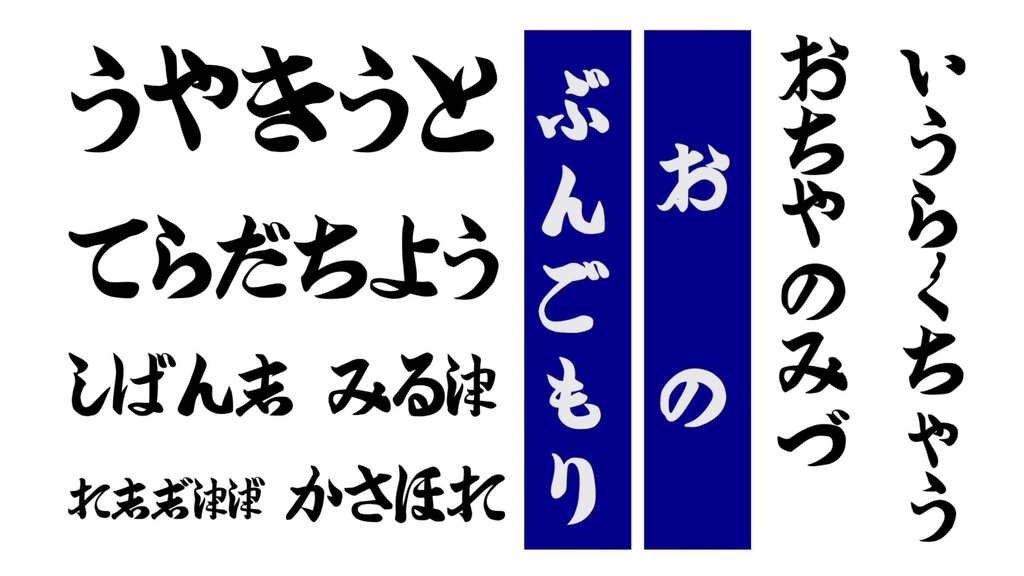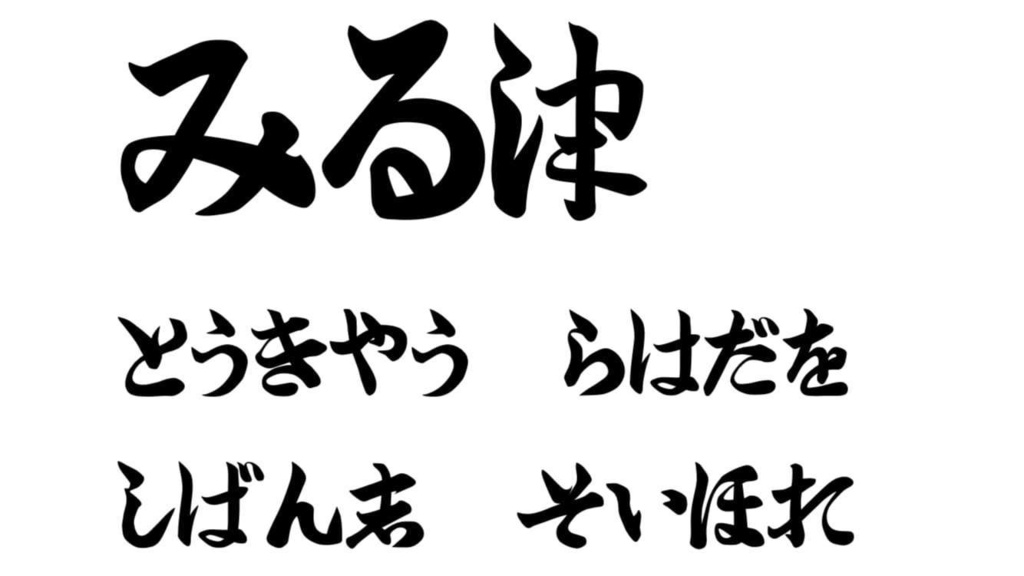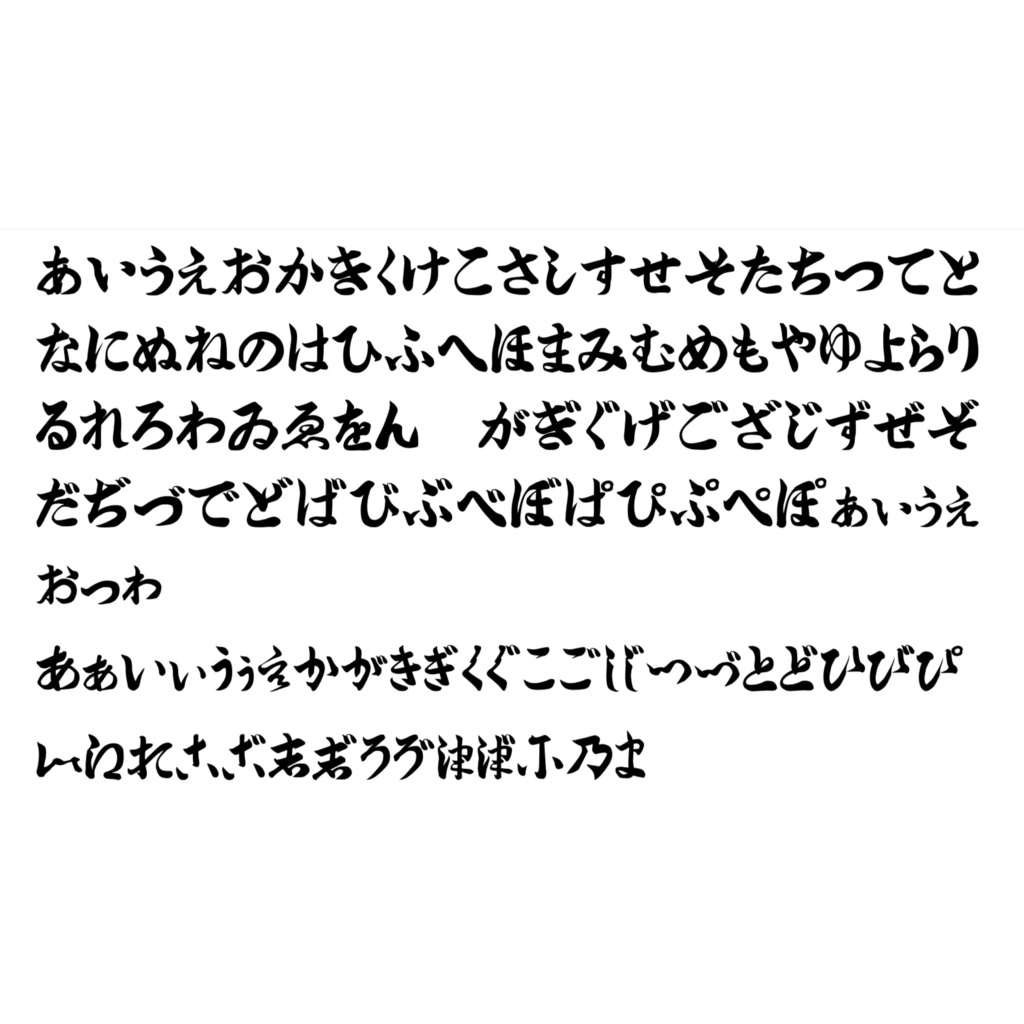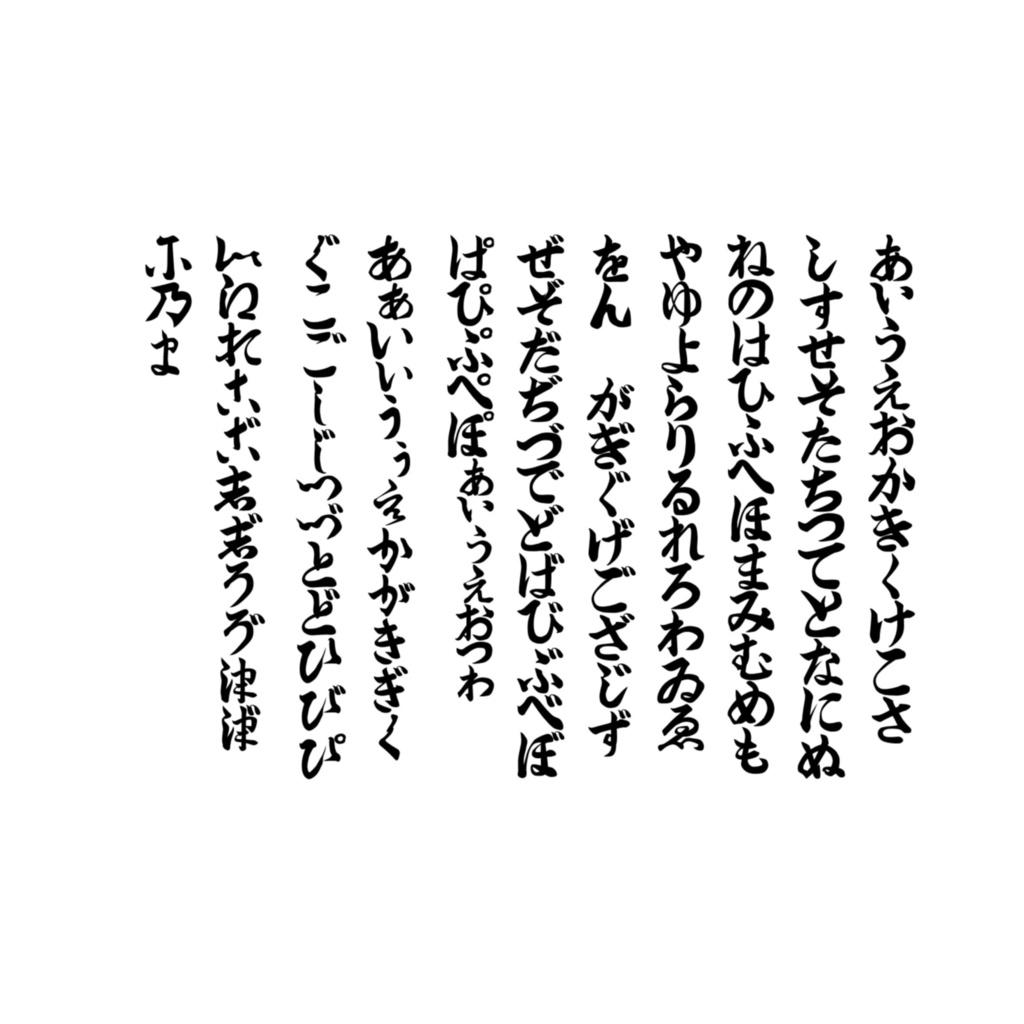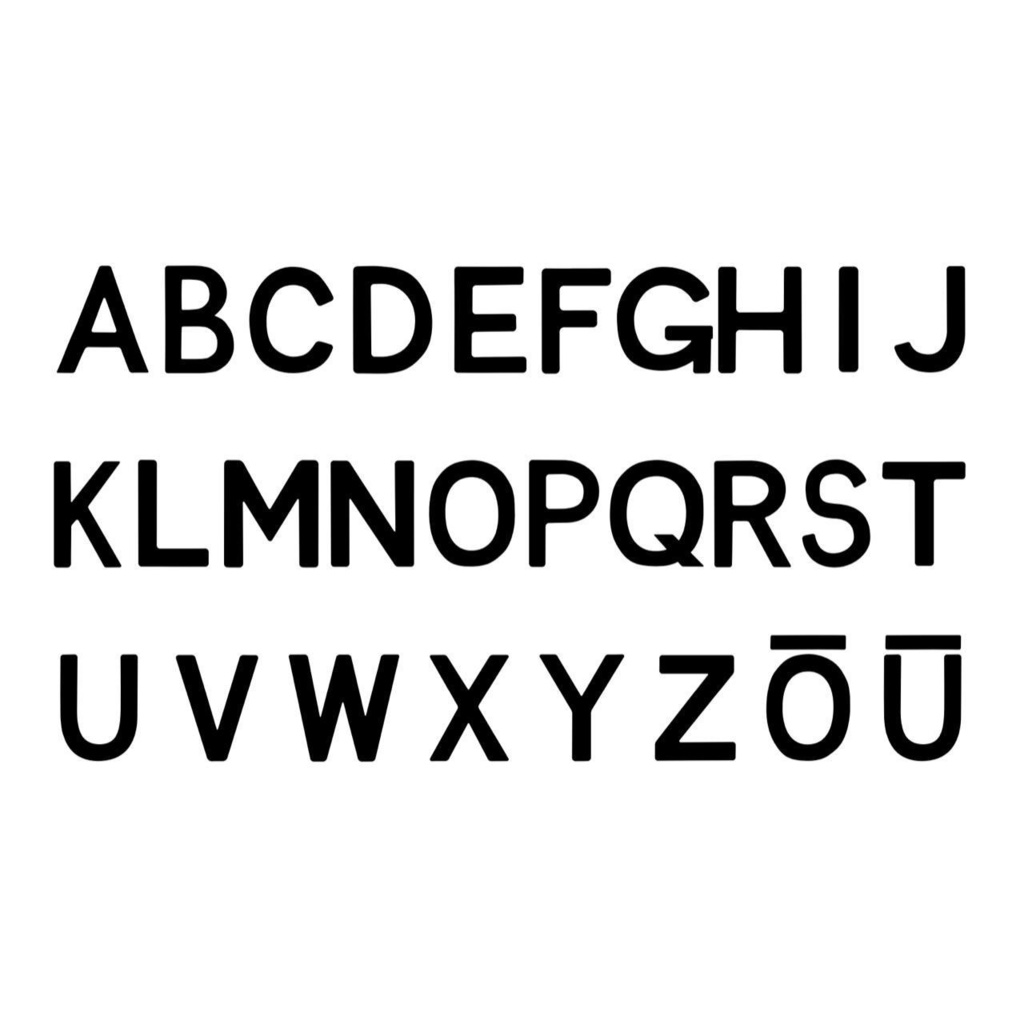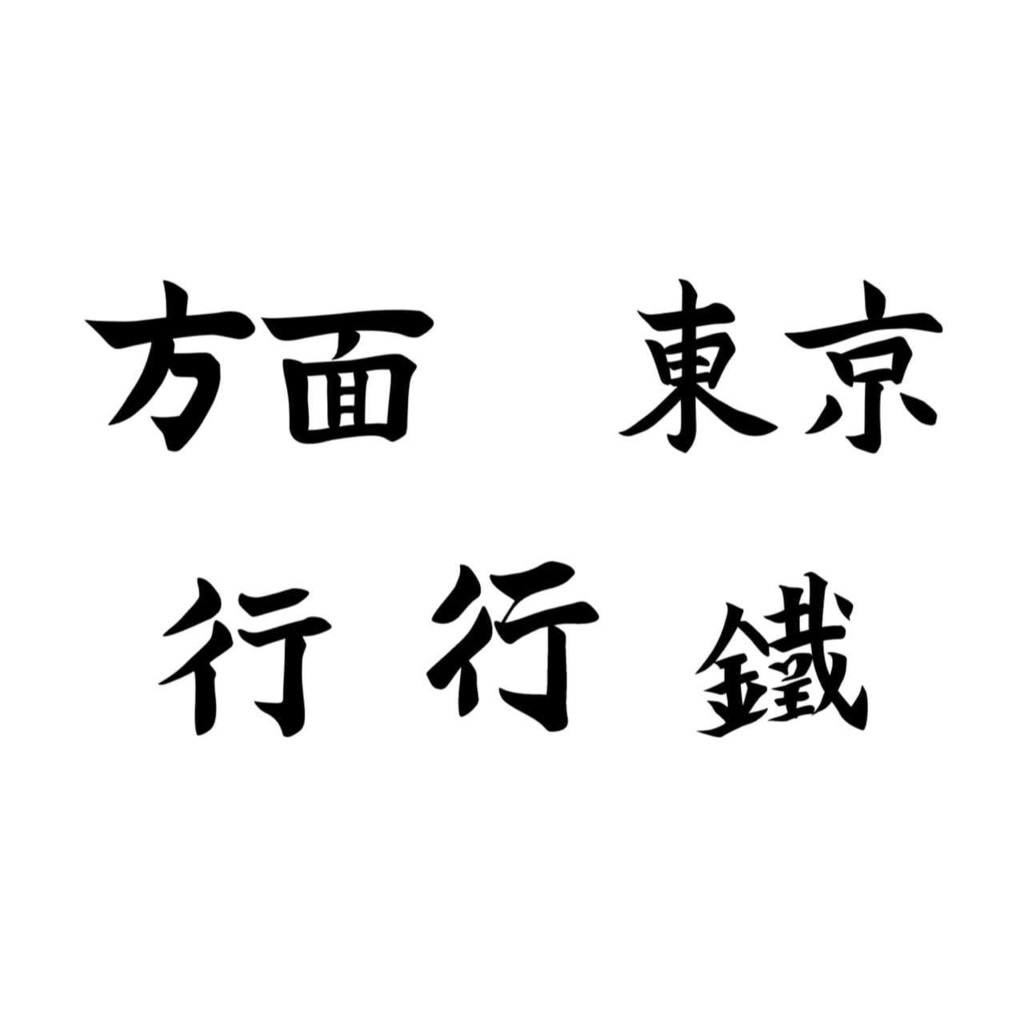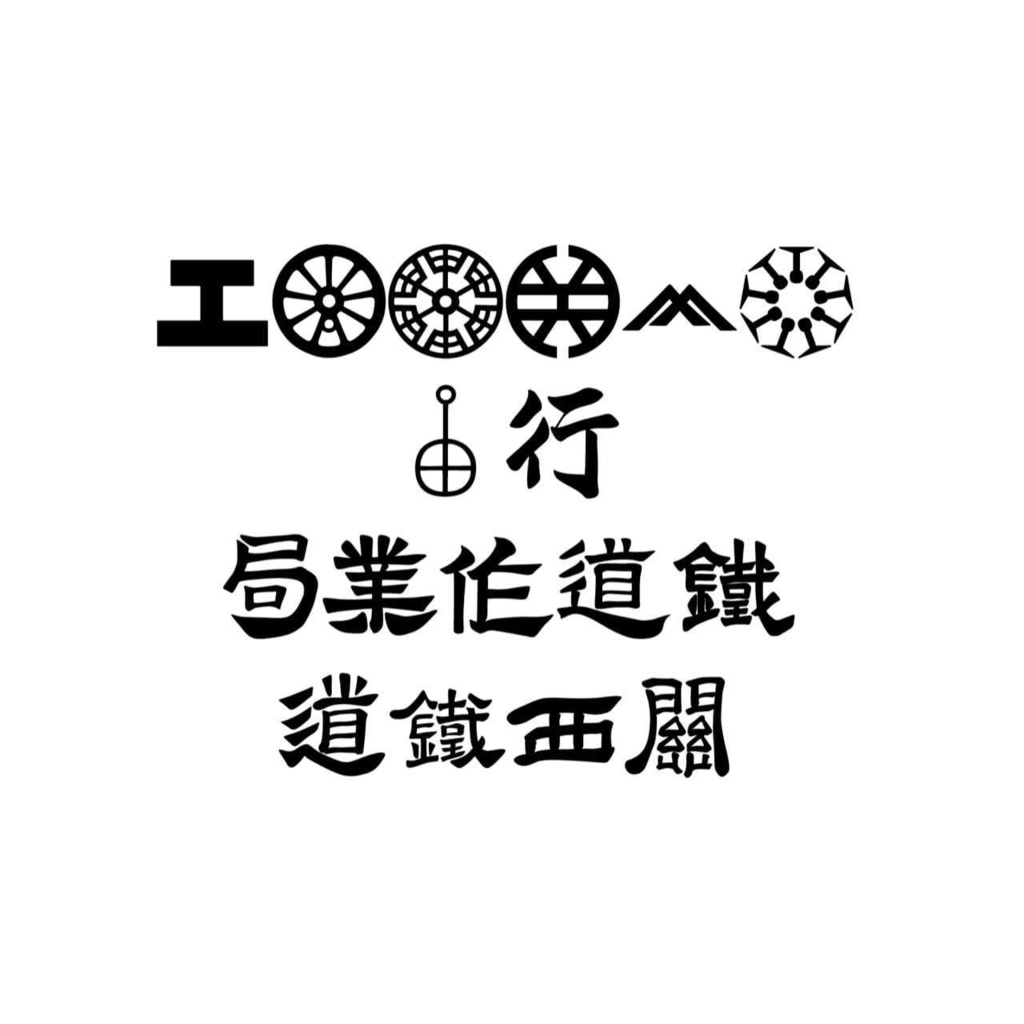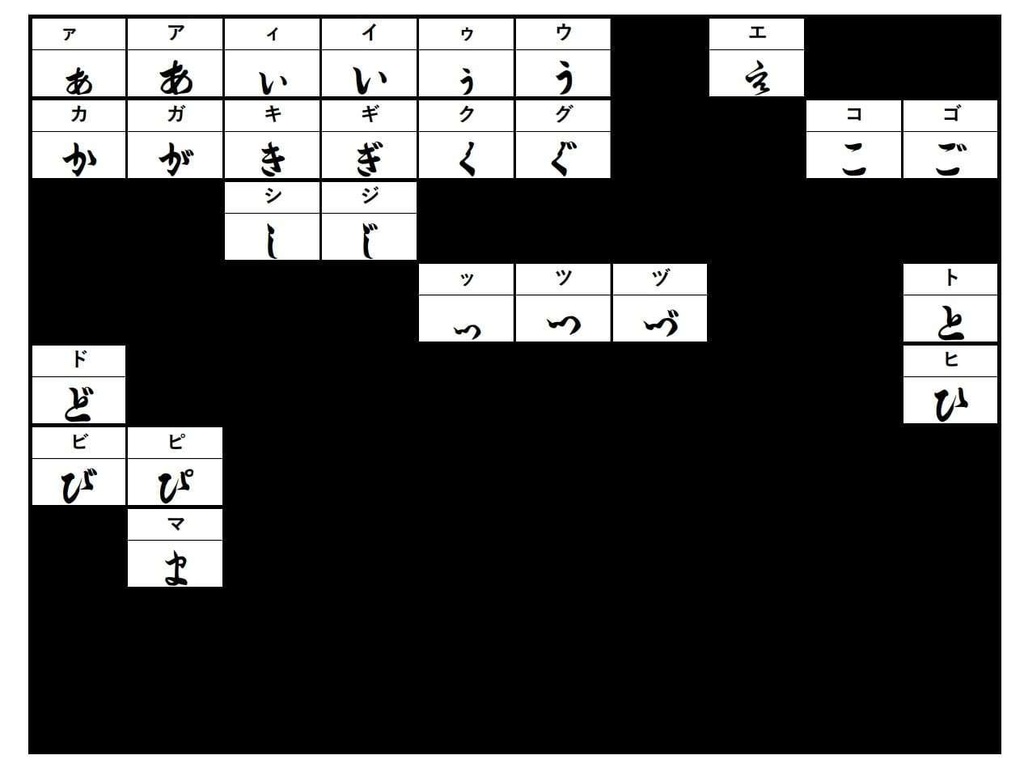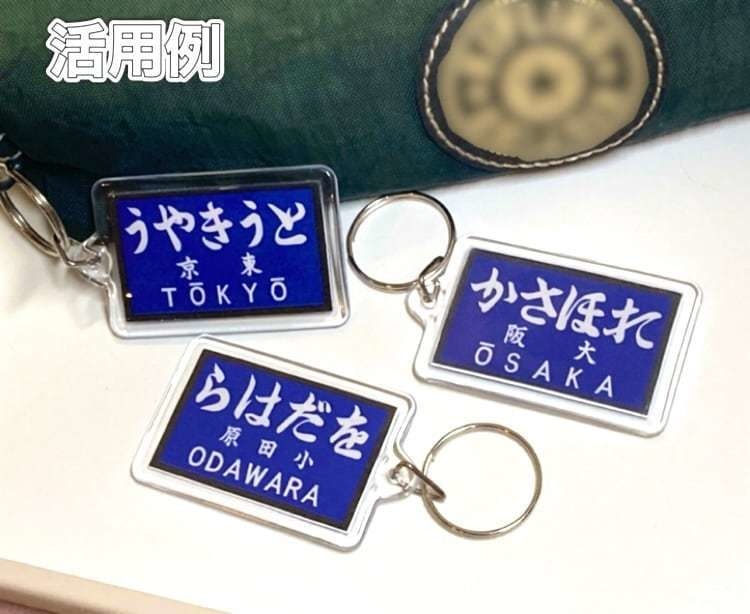
筆文字駅名標フォント
利用規約を必ずお読みください。 【注意】無料版(noteにて配布中)で動作に支障のないことを確認してから有料版を購入されることを強くおすすめします。 明治初期の鉄道創業から、大正昭和、そして戦後の昭和35(1960)年、国鉄におけるスミ丸ゴシック制定まで、駅名標や各種看板に第一線で重用された、太字で力強く、ところどころ古風な筆致の筆文字をフォント化しました。 平仮名五十音(一部の仮名は二種類)+変体仮名+漢字7字+アルファベット26字+O、Uのマクロン(長音記号)つき+オマケ(私設鉄道社紋や標記)16字 を収録したttfファイルです。 【無料版配布ページはこちら】 https://note.com/kan3kur3chann3l/n/nee541f1a4d21 また、下記URLのnote記事にて本フォントの詳しい説明もしております。併せてご覧ください。 https://note.com/kan3kur3chann3l/n/n88d605f0a3e6 ※商品画像の「小涌谷」は市販の別のフォントを使用しています。「筆文字駅名標フォント」には収録していません。ご注意ください。 1.現状動作確認が出来ているのは、作者の環境であるWindows11のみです。その他の環境での動作の確約はできません。 2.(2024/11/18改定)macOS 14.5にて動作確認ができました。Macでもお使いいただけますが、不具合が発生した場合の修正は遅れます(作者がMac環境を持っていない為、知人に確認してもらいながら対応することになります。)。 3.他の環境で導入、使用できないなどありましたら、作者にご一報ください。可能な範囲で対応しますが、技術が拙いため、対応しきれない可能性があることをお断りしておきます。対応できなかった場合は御返金致します。 4.有料版購入後の返金は原則お断り致します。無料版(noteにて配布中)で動作に支障のないことを確認してから有料版を購入されることを強くおすすめします。「3」に記載の状況など、事情のある方は作者までご相談願います。 5.表示が崩れる、見た目が汚いなどありましたら、作者Twitterか本記事のコメントにてお知らせください。なるべく早く修正致します。 6.作者を明示しない、自作を騙った二次配布や改変は禁止致します。 作者を明示した上で、無料版を有料版に準じた内容に改変する等、当方の利益を侵害するものでなく、かつ非営利での改変、またそれらの成果物の配布はご自由に行なって頂いて構いません。 問い合わせは義務ではありませんが、当アカウントに一言下さればうれしいです。営利目的の改変、配布は作者にご相談下さい。 本フォントを使用した模型、映像、イラスト、CG作品などの成果物を公表する際には、キャプションやエンドクレジット等に「筆文字駅名標フォント」の名称と作者ハンドルネーム「鴨」或いは「X(旧Twitter):@kan3kur3chann3l」を明記して下さると励みになります。